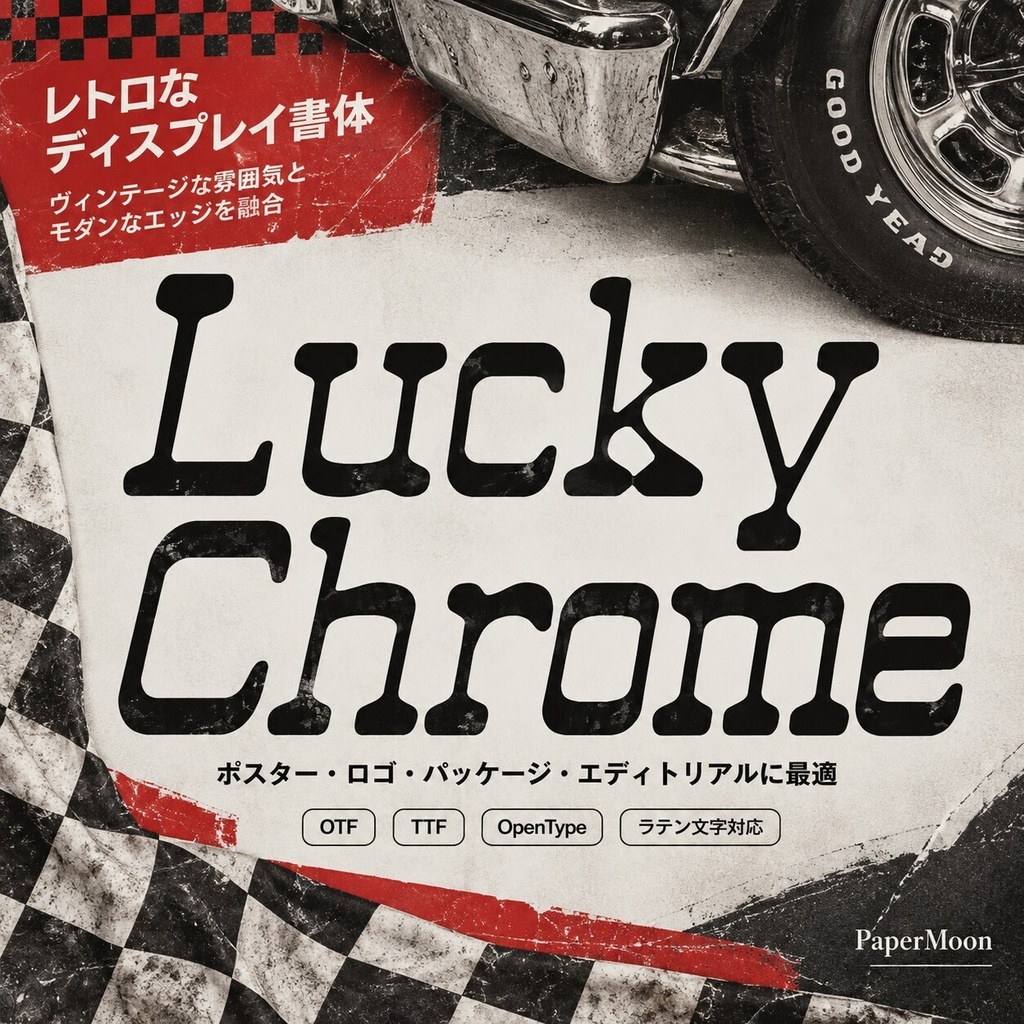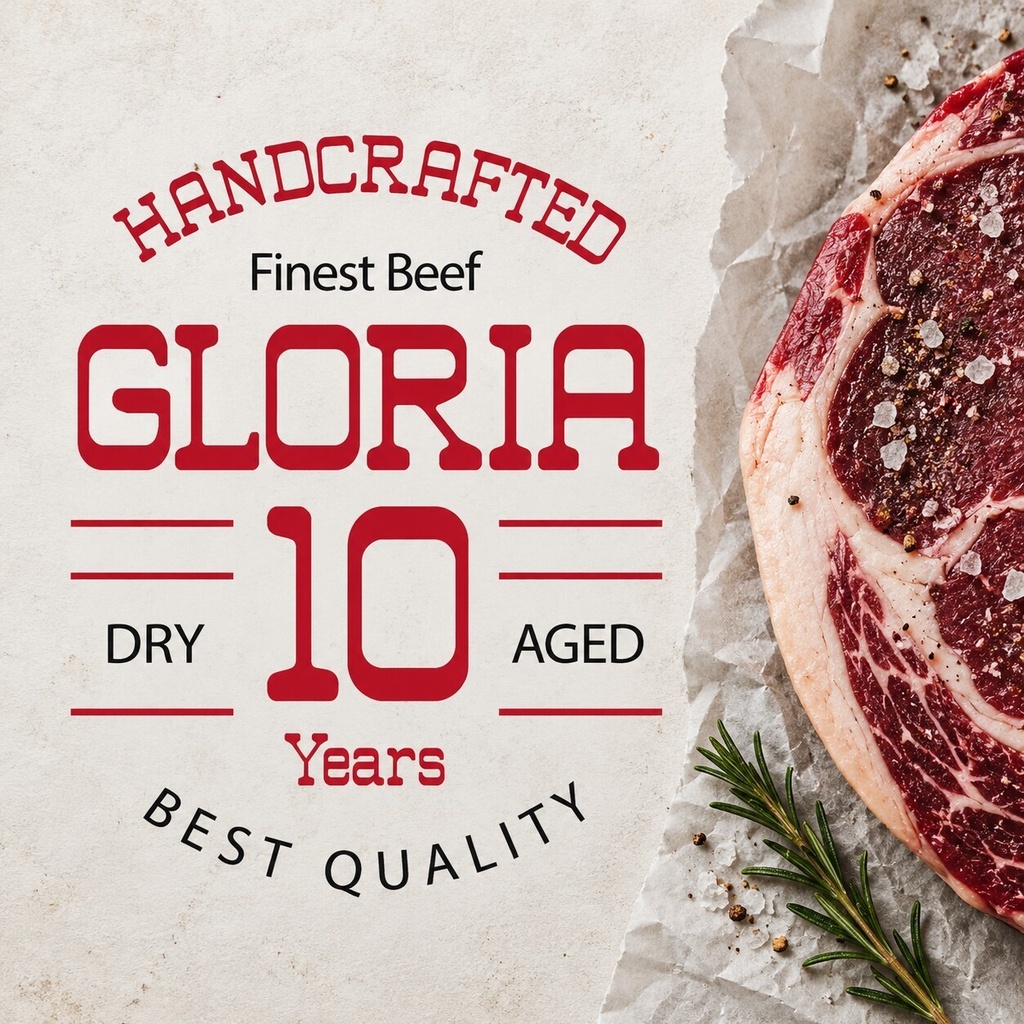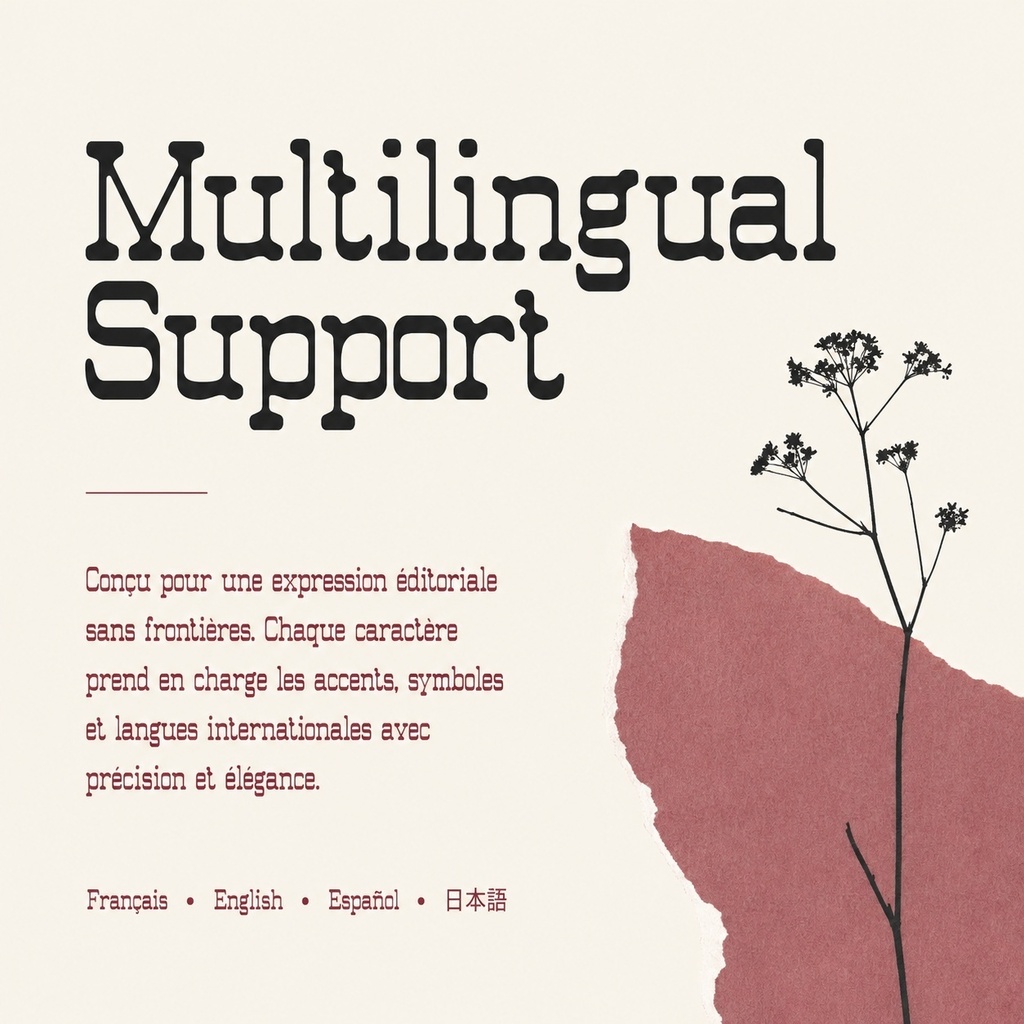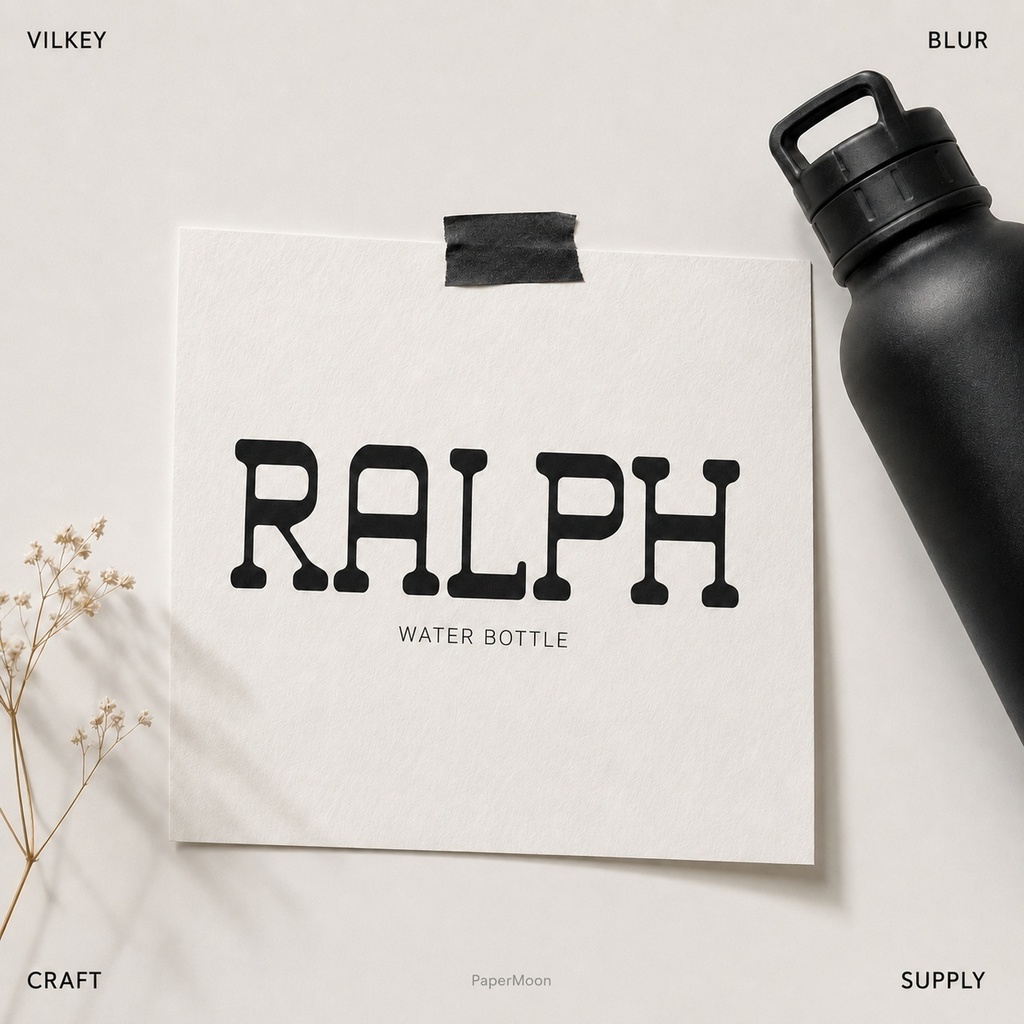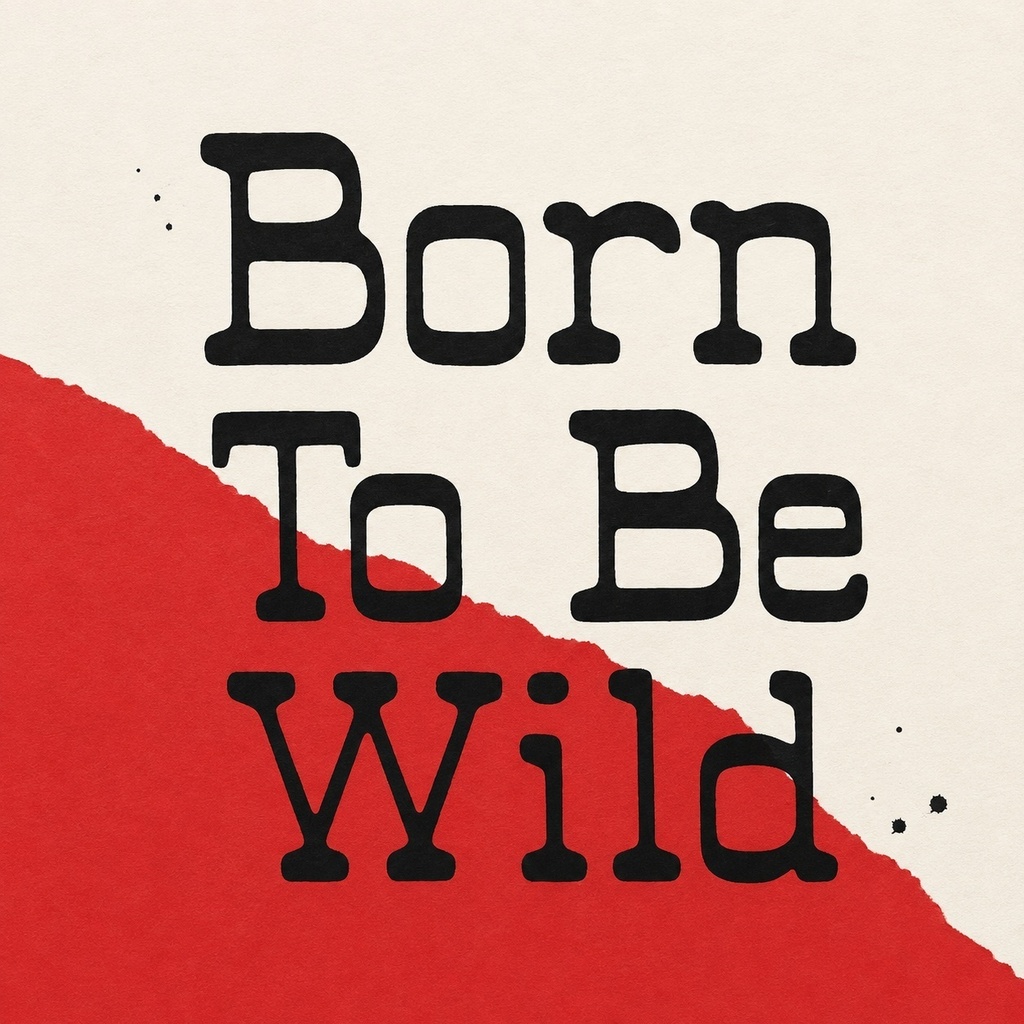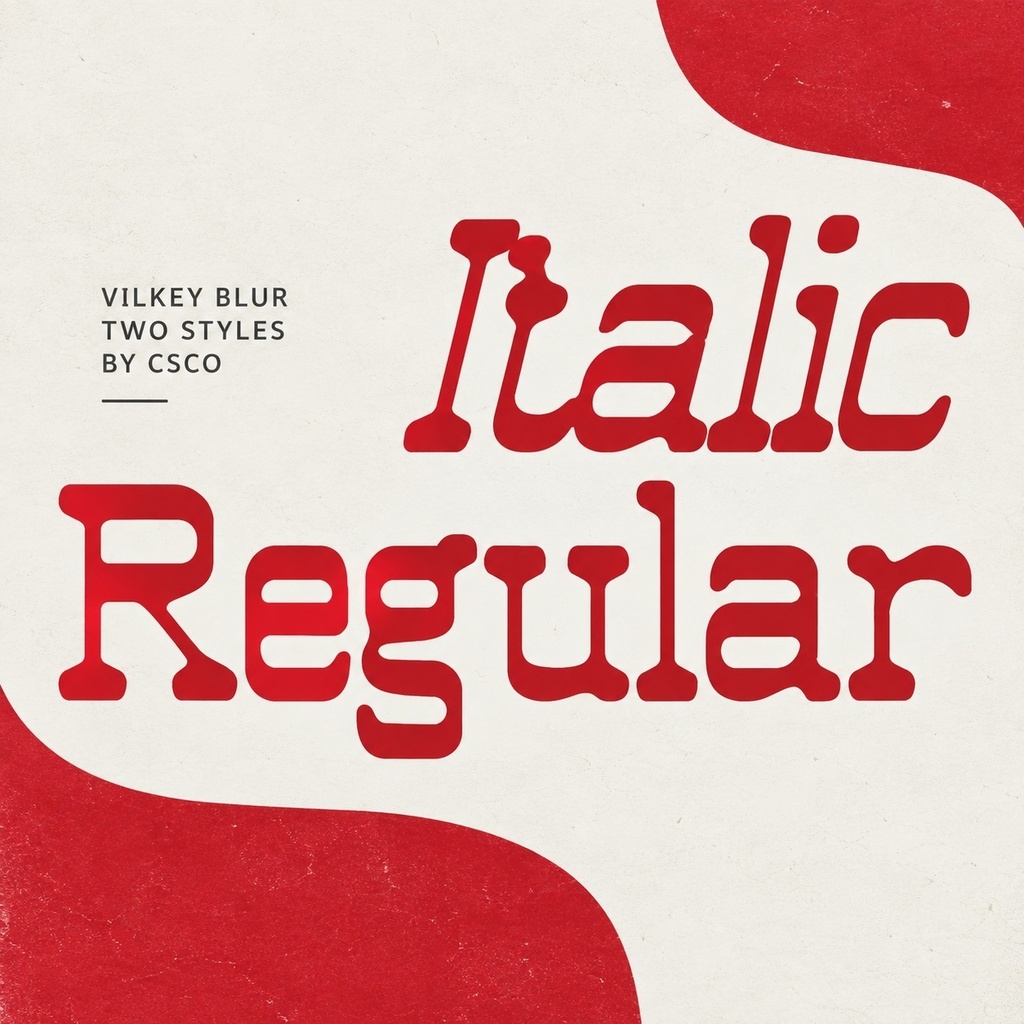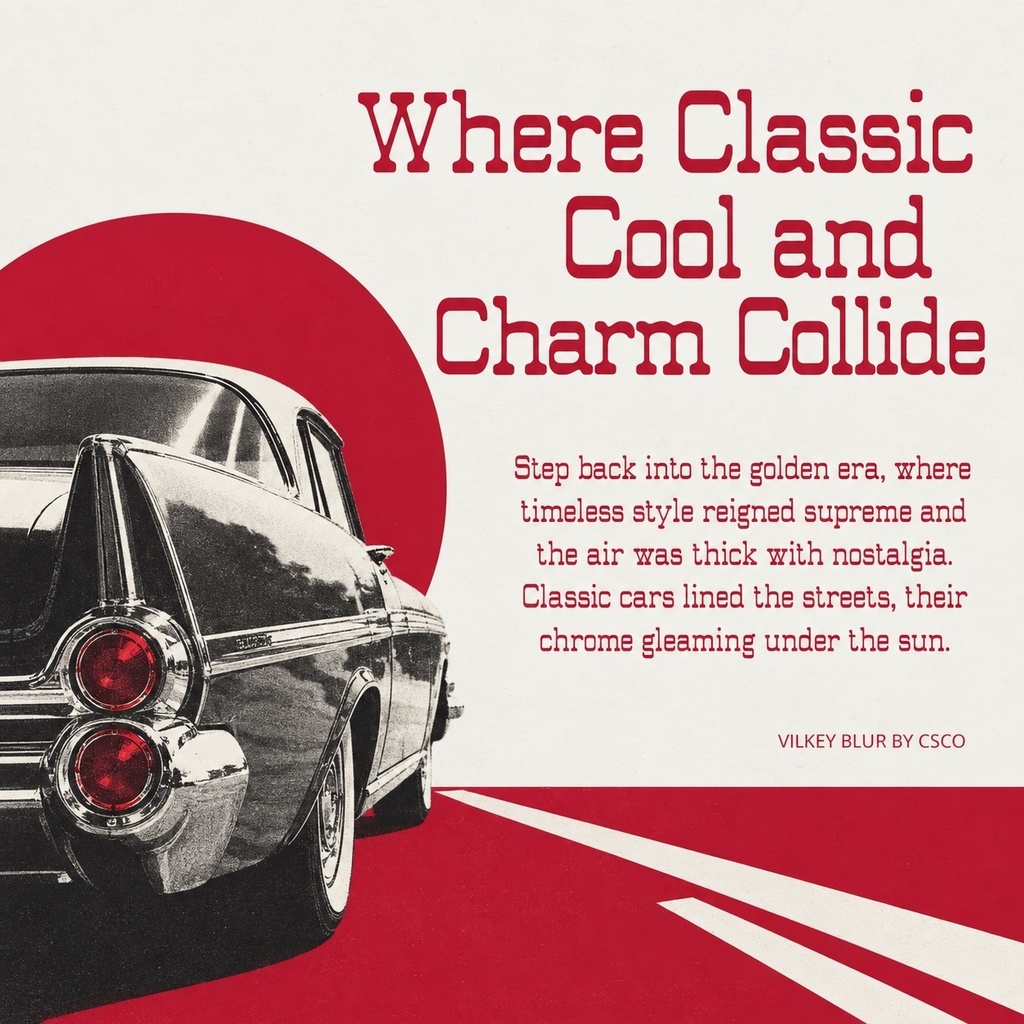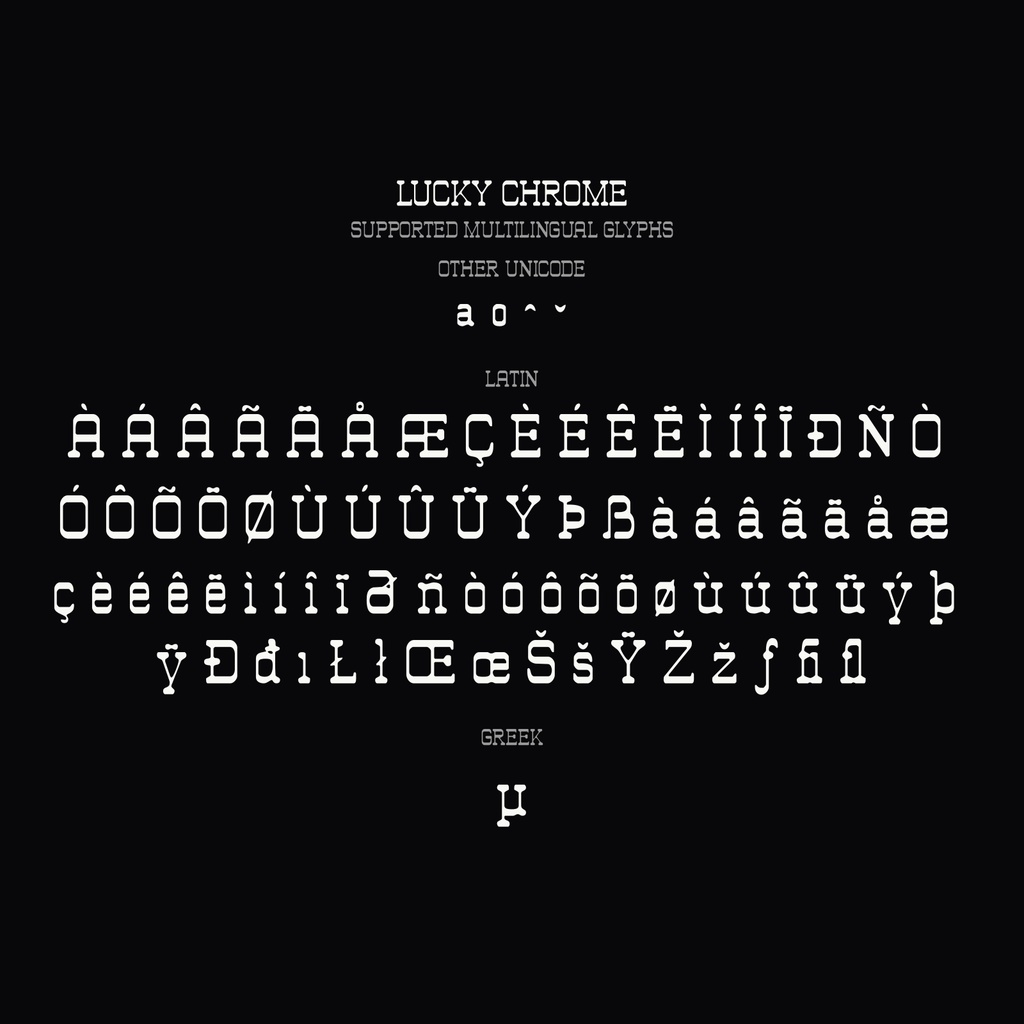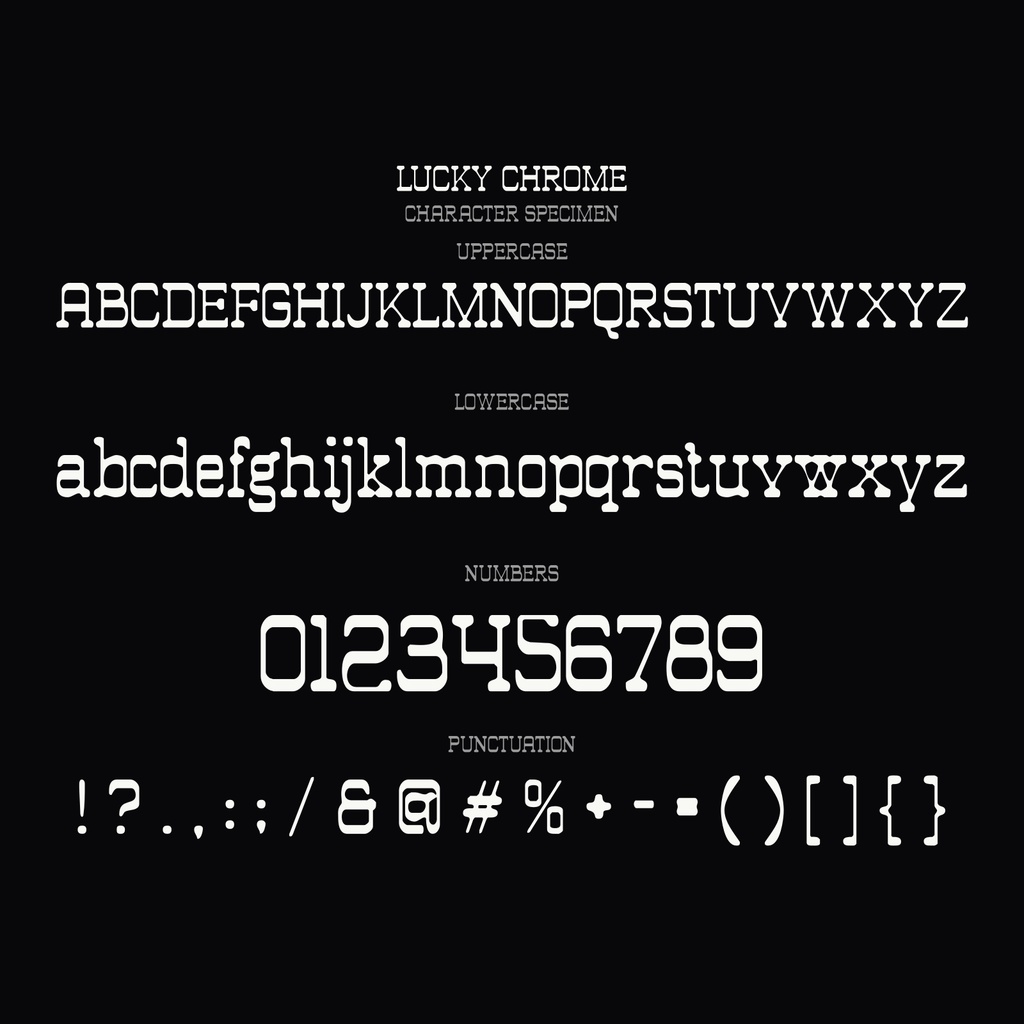
Lucky Chrome|ぼかしと逆コントラストの欧文セリフフォント
Lucky Chromeは、力強いスラブセリフ、ドラマチックな逆コントラスト、やわらかなぼかし表現を組み合わせた欧文セリフフォントです。 通常のセリフ書体とは異なり、文字の下側を厚く、上側を細くした逆コントラストが印象的な骨格をつくります。ブランドのロゴや広告、タイトル・見出しなど、短い言葉を強く見せたいデザインに向いています。ぼかしのやわらかさと厚みのあるセリフが、硬質さだけに寄らない独自の存在感を演出します。 収録バリエーション Regular Italic 収録内容 英字の大文字・小文字 数字・句読点などの基本記号 多言語アクセント OpenType形式、TrueType形式 PUAエンコーディング 特別なソフトウェアは必要ありません。ブランド名、広告見出し、タイトルロゴ、短いキャッチコピーなどのレタリングにお使いください。 本商品は有料デジタルフォント商品のため、販売価格、購入後の利用条件、ライセンス表記は販売者がBOOTHの商品設定と利用規約に合わせて入力してください。